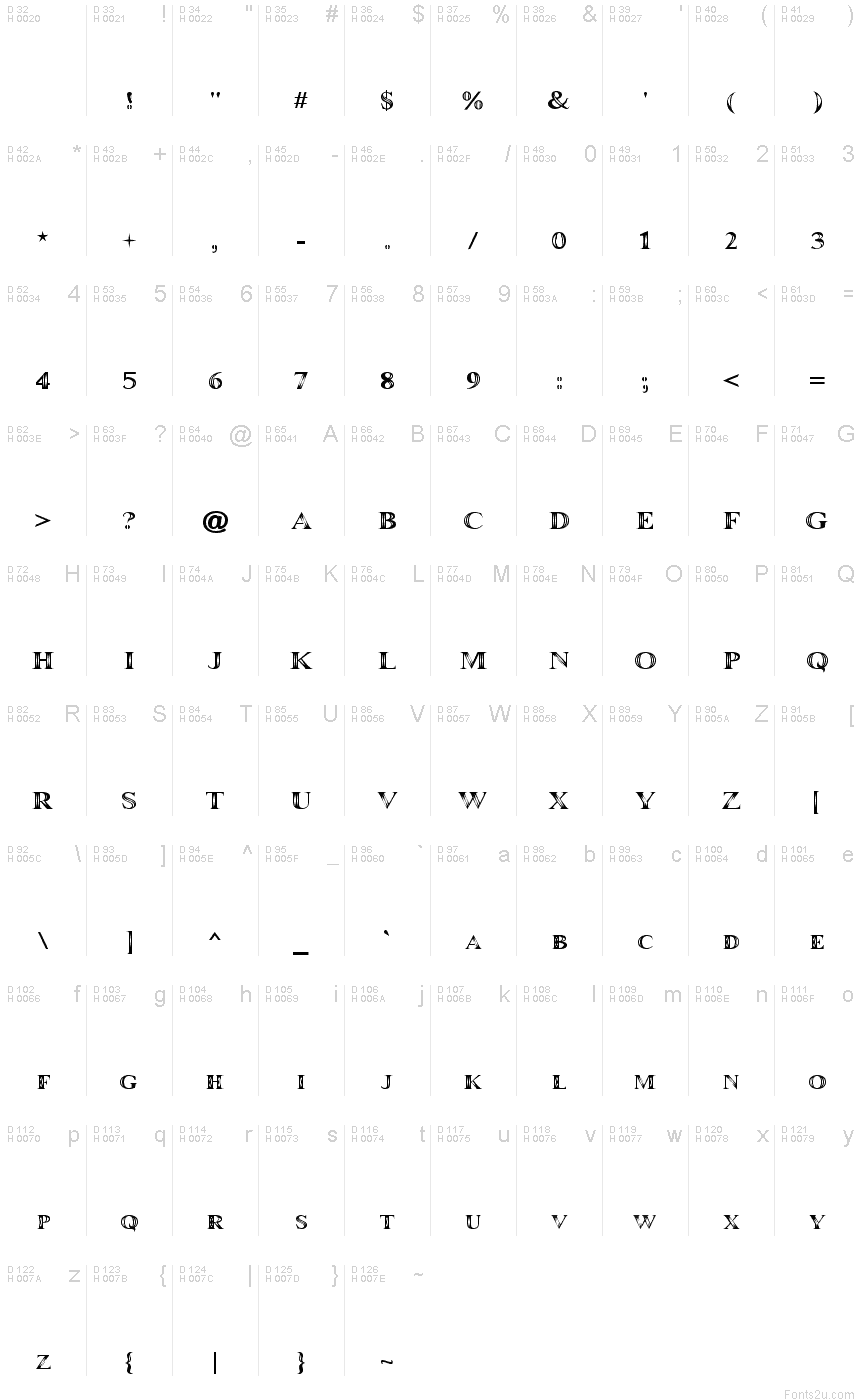
Maranallo
Maranallo od GemFonts98 to darmowy, retro font typu display o wysokich, wąskich literach, z ostrymi szeryfami klinowymi i dekoracyjnymi, rozdzielonymi kreskami, które nadają formom rytmiczny, gotowy na plakat wygląd. Zaokrąglone R i kanciaste A zachowują ten sam pajęczy kontrast, dzięki czemu rodzina krojów jest ozdobna, ale nieprzeładowana.
Maranallo świetnie sprawdza się w projektach logo, opakowaniach w stylu vintage, tytułach filmowych, grafikach albumów oraz akcentach redakcyjnych, gdzie stylizowany szeryf sprawdza się lepiej niż zwykły krój do tekstów. Jej dekoracyjna struktura pasuje również do zaproszeń, projektów etykiet i krótkich napisów, które potrzebują wyrazistego stylu retro.